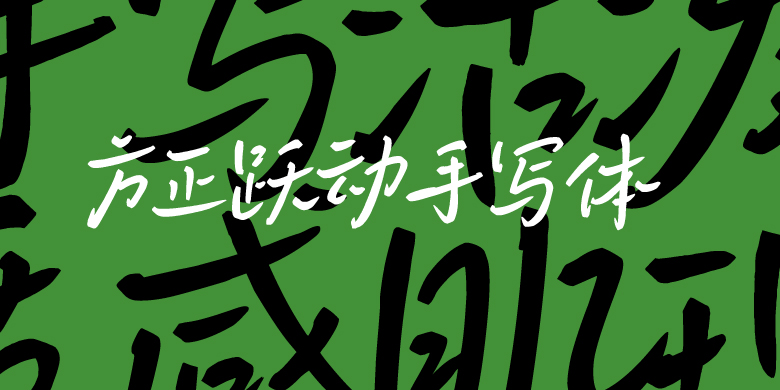
方正跃动手写体
万紫千红总是春
七八个星天外,两三点雨山前。
旧时茅店社林边,路转溪桥忽见。
周佳敏
创意书写
跃动手写字体以“年轻活力,跃动青春”为理念,字体整体字间距排布松弛透气,风格元气鲜活、轻盈跃动、青春治愈,整体视觉干净清爽、灵动有张力,精准适配青春、成长、热血、热爱、自由的主题表达。既能满足年轻化潮流审美,又能精准传递积极向上、肆意生长的青春内核,适配绝大多数年轻活力向创意设计场景。